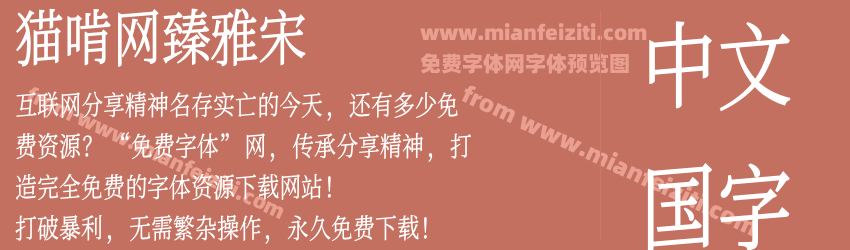
猫啃网臻雅宋是基于思源屏显臻宋改造的类仿宋体字形。由于现在可以免费商用的仿宋体字形十分短缺,所以猫啃网网友@新愚公利用业余的时间把思源屏显臻宋通过程序进行改造,压缩字体宽度,并把字体向上拔高,有点类似仿宋字形。看过来效果还不错,特意分享出来供有需要的朋友使用。
本款“猫啃网臻雅宋”是一款书写很新颖的字体,字体大方,适合各种设计作品使用!欢迎下载!